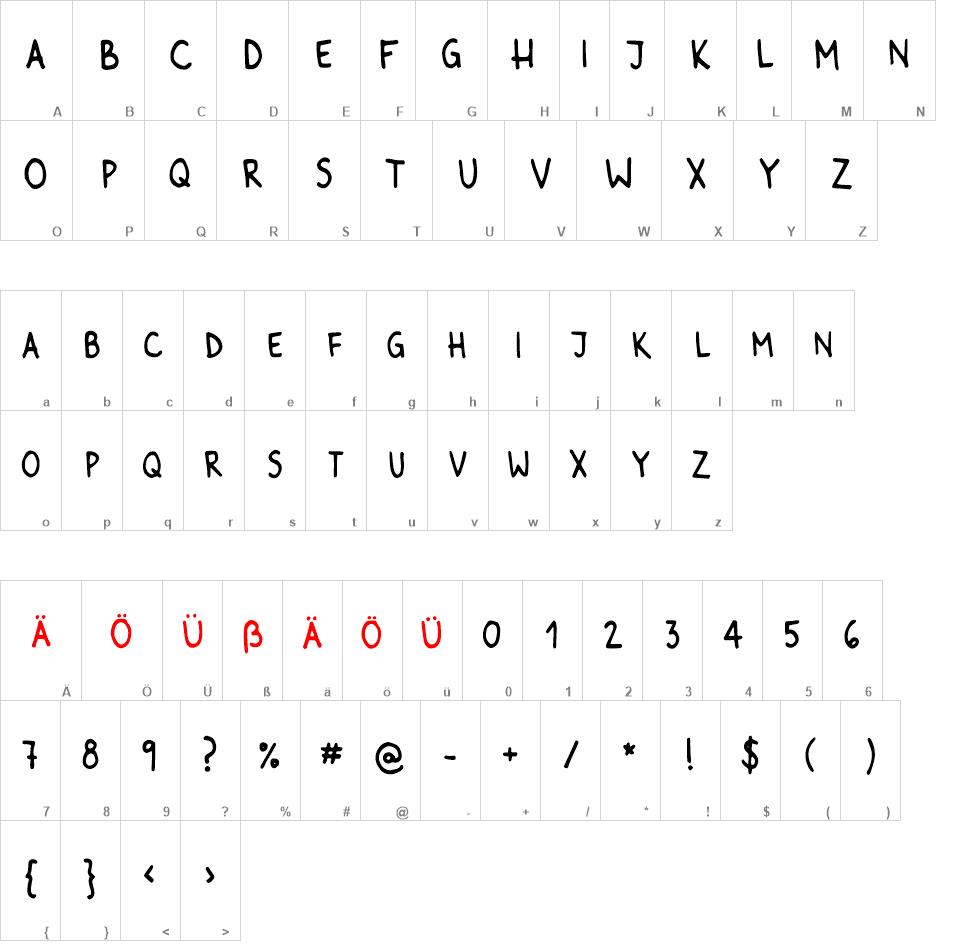
Stop Yelling
Stop Yelling font
Stop Yelling
HÖR AUF ZU SCHREIEN! v1.0
Eine nicht aggressive Schriftart mit gut gemachten Großbuchstaben, vollständigen Interpunktionszeichen und Zahlen, unglaublich einfach zu lesen. Für Englisch, Deutsch, Spanisch, Französisch, Norwegisch, Portugiesisch, Slowenisch und alles dazwischen. Kleinere Fälle sind völlig unterschiedlich und Sie werden sogar die Option für randomisierte Zeichen finden, um ein hervorragendes Ergebnis für Textblöcke oder einfache Zeilen zu erhalten.